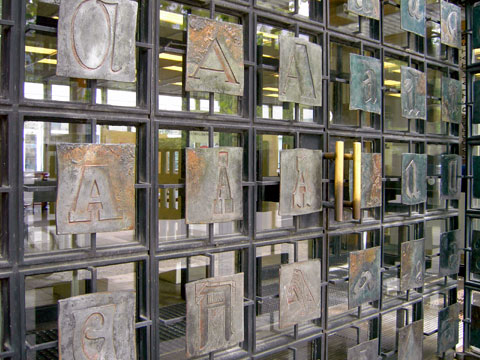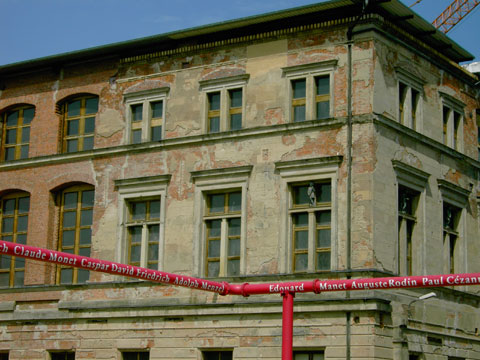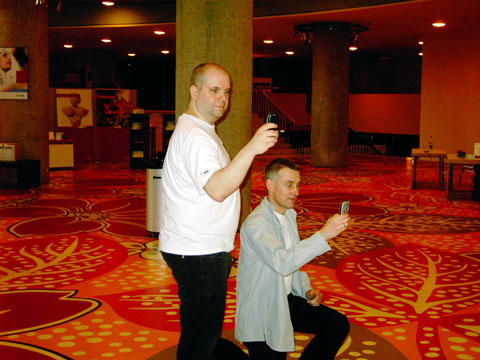
TYPO Berlin 2005
Vom 19. bis zum 21. Mai 2005 fand die 10. internationale FontShop Konferenz TYPO Berlin statt. Die Werbung dafür klang ganz spannend: Erik Spiekermann würde zum letzten Mal Organisator sein, FUSE-Konferenz Mitgründer Neville Brody nach vielen Jahren wieder eine Rede halten. Das passende Thema für diesen Wandel? „Change“, selbstverständlich.
Unter den 1.000-oder-so Besuchern der TYPO sind immer ganz viele Studenten. Wie letztes Jahr waren einige der HfG Offenbach beim Event in der Hauptstadt dabei. Darüber berichtet Roman Köller (4. Semester, VK) in seinem TypeOff-Debut.
Blue Sky, Blue Sky
Roman Köller
Erwartungsgemäß besuchte man bei der TYPO Berlin eine Massenveranstaltung. Circa 1300 Teilnehmer stellten ein Riesenpublikum dar. Die Sprecher wurden in drei Säle verteilt, die man, ja nach Interesse besuchen konnte. Der vollstündliche Vortragsbeginn (gute Idee) wurde jedoch nicht immer eingehalten, so dass es zu Verzögerungen und Anschlussproblemen kam.
Ich war überrascht wie viele Sprecher ihre Redezeit als Werbezeit verstanden und das Konferenzthema „Change“ ignorierten.
Nicht so Juli Gudehus. Sie stellte die Ergebnisse ihres eigens initierten Projektes vor. Die Reihe der Redesigns einer Strumpfhosenschachtel, angefertigt von deutschen Design Büros im Sinne von „Hans im Glück“ weist interessante Reaktionen der Gestalter auf den jeweils vorangegangenen Entwurf auf. Manchmal, zugunsten der Wiedererkennung leicht korrigiert, manchmal brutal verworfen, zeigt sich, dass insbesondere bei Markenkommunikation „Change“ viel Fingerspitzengefühl voraussetzt.
Marc Grauel, Autor bei brand eins sprach in seinem anspruchsvollen Vortrag von physischer und geistiger Metamorphose, vom Streben des Menschen von Transformation in sein Ideal. Grauel zeigte u.a. einen Spot für die US Marines. Dieser setzt voll auf Transformation und zeigt den einzelnen Soldaten als glorreichen Superhelden. Change als Werbeargument.
Albert Jan Pool skizzierte den Weg der FF DIN von der Hausschrift der preußischen Eisenbahn über die DIN 1451 während des Wirtschaftswunders bis hin zu ihrer heutigen, leichteren Form mit Textqualität.
Gerard Unger lud ein zur Typo 1005. Bilder europäischer Inschriften bewiesen die Existenz vielfältiger Ligaturen und Formvariationen vor OpenType. Das typografische Gesicht der Romanik besitzt wunderbare Züge.
Chip Kidd (Buchcover für Randomhouse) lieferte Entertainment pur. Anschaulich schilderte er, wie er verzweifelt wenn er „Blue Sky, Blue Sky“ hört. Mit „Völliger Freiheit, Alles Gut“ ist schwer für ihn umzugehen. Viel lieber bekommt er vom Auftraggeber Hinweise, (die er dann ignorieren kann). Der beschriebene Auftrag für ein Poster für Adobe legte dem Publikum zusätzlich die eigenwillige kalifornische Redensart offen.
In der Kritikrunde wurde der Hang der Sprecher zur Vorführung der eigenen Arbeiten angesprochen. Mehr inhaltliche Reflexion wäre wünschenswert. Eventuell in einer geleiteten Diskussion mehrerer Persönlichkeiten zu speziellen Themen. Den Vorschlag kommentierte Spiekermann damit, dass das Publikum zum Teil nur „gucken“ wolle, zum anderen Teil tiefe Erörterungen hören wolle. Beidem gerecht zu werden sei unmöglich. Diskussionsrunden habe es nicht gegeben, weil man nicht gewusst hätte, wie die einzelnen sich untereinander verstehen würden. Außerdem würde der große Saal so etwas auch nicht zulassen. Im Übrigen bedauere man, dass viele nicht das Thema aufnehmen. Darauf hätte man aber keinen Einfluss. Es erschien mir, dass das Organisationsteam für Lob empfänglicher war als für Kritik, zumal sämtliche Programmverzögerungen auf Mac OS Tiger geschoben wurden. Blue Sky, Blue Sky.
Von der Konferenz selbst habe ich keine guten Fotos. Hier sind drei, die alle am Rande entstanden sind:
Florian und Bernhard von Linotype fotografieren den Linotype Messestand.
Anke fand diese Fassade irgendwo in Ostberlin.
Dieser Schriftzug war auf der Museumsinsel zu sehen.
2. Bei den Kollegen von Slanted findet man noch einige Fotos:
Ich war ja nur letztes Jahr auf der Typo und fand damals zumindest die Qualität der Vorträge teilweise mies bis hin zu fade Selbstdarstellung. Wenn schon Selbstdarstellung, dann lobe ich mir den Auftritt von House Industries (http://www.houseindustries.com), das macht wenigstens noch Spaß. ;)
3. ich hab beim Fontshop Blog noch was gefunden:
Die Auswertung des Fragebogens zur meinung der TYPO besucher:
Ich bin 2004 als Student dahingegangen, und fand die Studentenpreise doch OK (so lang als mann vor Weihnachten sich anmeldet…). Sonnst bin ich mit den anderen Kritikpunkte einig. Ich glaube, dass die Punkte jedes Jahr das Gleiche sind.